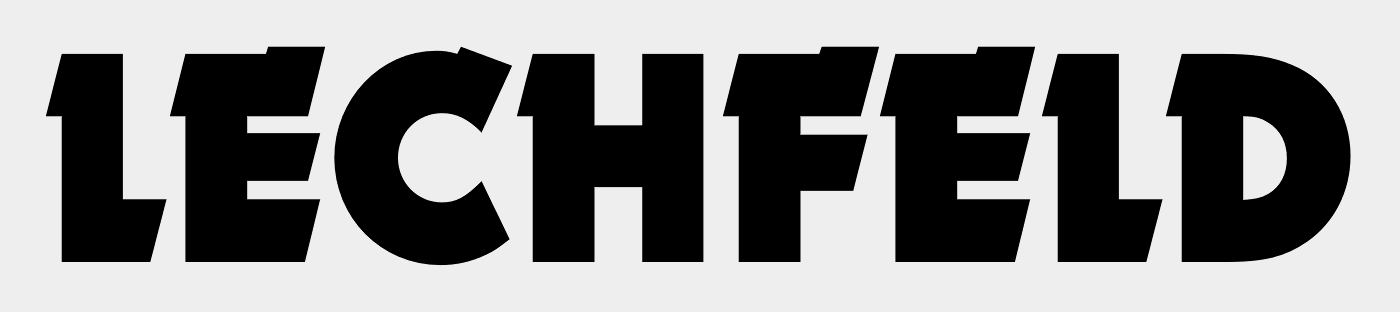
Suche Schriftart von "LECHFELD BEBEN"
kennt jemand die Schriftart von "LECHFELD BEBEN"?
Es handelt sich dabei um den Namen einer Party der KLJB Rehling (einem Verein der Gemeinde Rehling in Bayern).
Die Qualität der Datei ist leider sehr schlecht, aber die Schriftart ist recht auffällig...